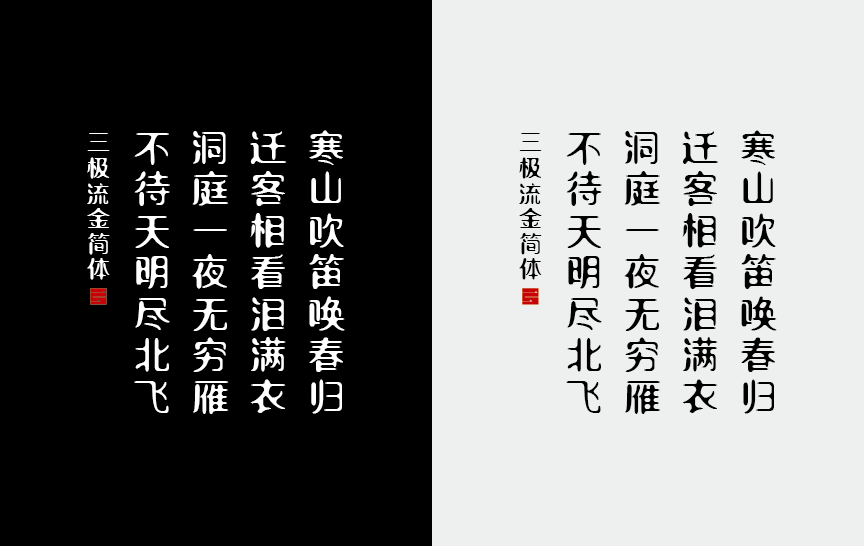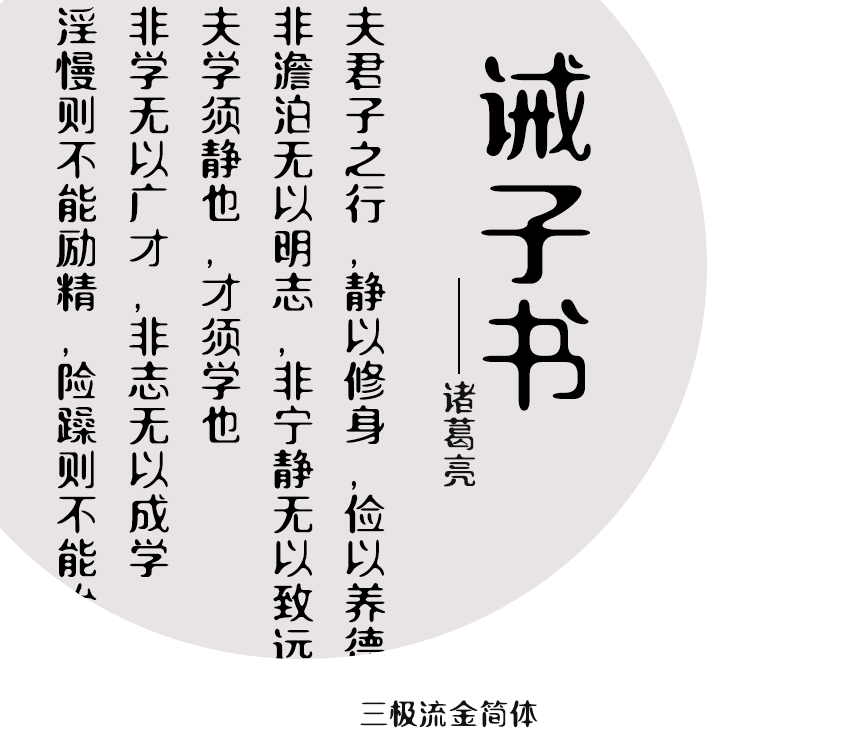
三极鎏金简体
苍苍水气合遥天
蔡荣富
三极鎏金简体,这款字体最初的构想来源于毛笔字墨水不均、被水滴晕开后的样子。它由曲线所构成,笔画与笔画衔接处大多为圆角,且呈现水滴镏金状,带有古典、质朴的气息。笔画底层结构源于黑体,丰富了目前市面上黑体的表现形式。适用于杂志读物、宣传册、品牌广告、包装设计以及社交网络个性化用字。